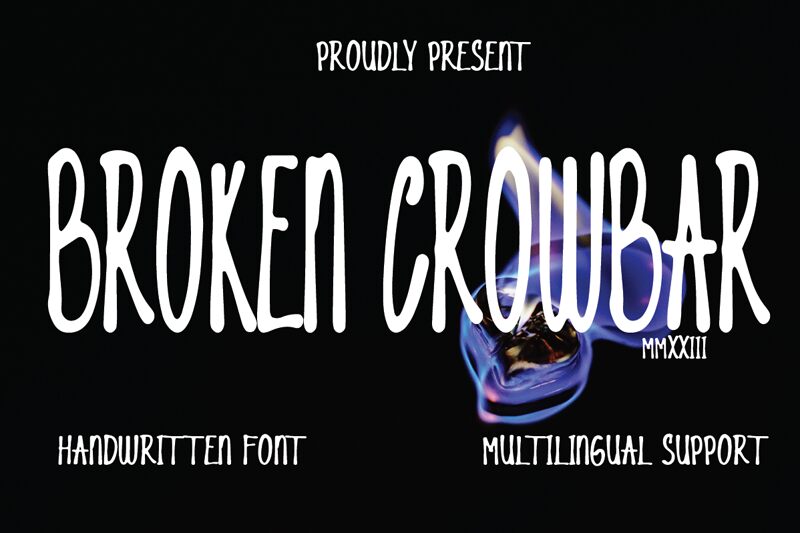
Broken Crowbar هو خط يدوي مجاني يتميز بحروف طويلة وضيقة وضربات دائرية تمنحه إيقاعًا سريعًا يشبه الرسم اليدوي. تظل الأشكال حرة وغير منتظمة قليلاً، مع جودة خط عفوية تمنع الكتابة من الشعور بالطابع الميكانيكي الجامد.
يعمل Broken Crowbar بشكل رائع في الملصقات، وتصاميم الاقتباسات، ورسومات التواصل الاجتماعي، وقوائم المقاهي، والهوية التجارية غير الرسمية التي تحتاج إلى لمسة شخصية. كما يناسب هذا الخط المجاني الملصقات القصيرة وتغليف المنتجات، لأن هيكله اليدوي البسيط يضفي شعورًا مباشرًا وواقعيًا دون الحاجة إلى زخارف إضافية.